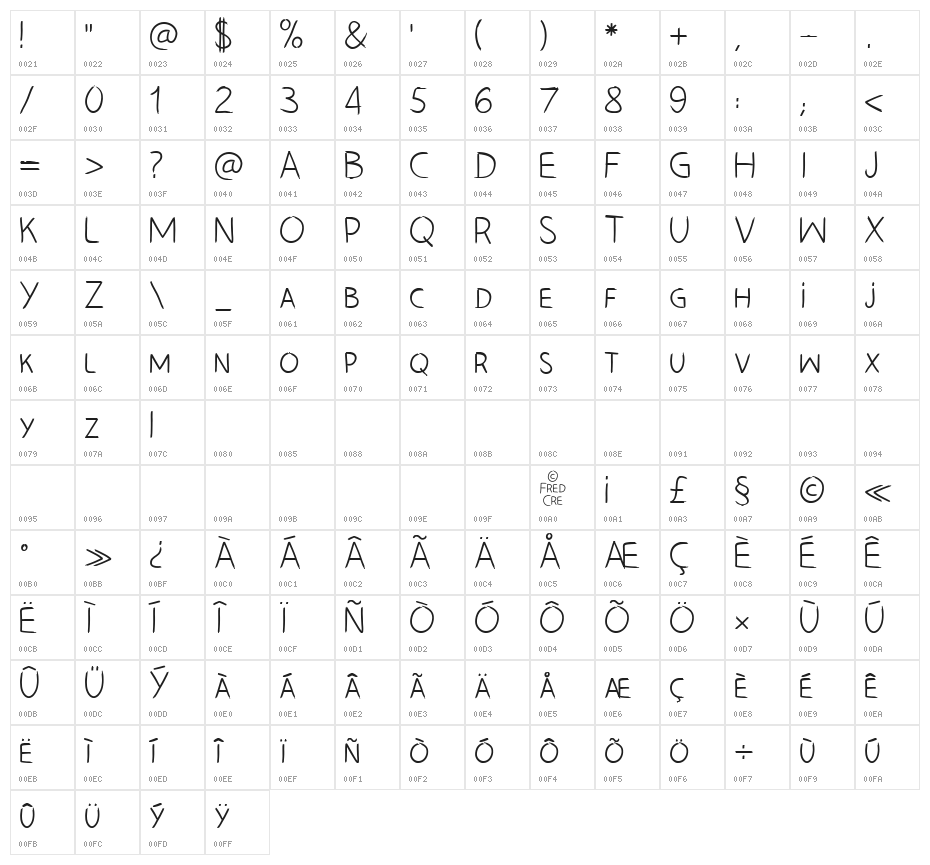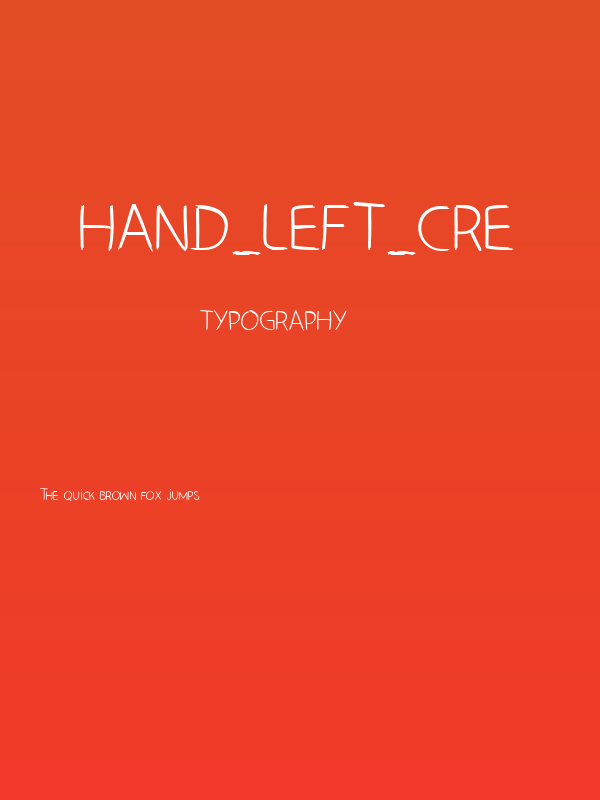
HAND_LEFT_CRE Font
| Gesamtstil | Casual, Playful |
| Anwendungsfall | Headlines, Informal text, Personal projects |
| Vorgeschlagene Projekte | Ideal for greeting cards, children's books, casual invitations, and personal branding. |